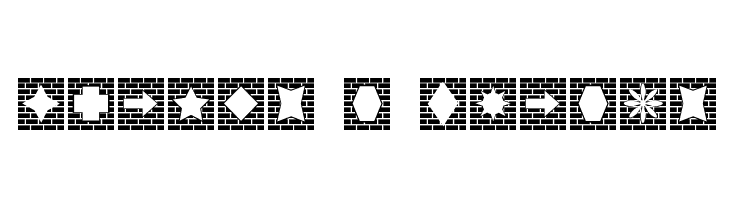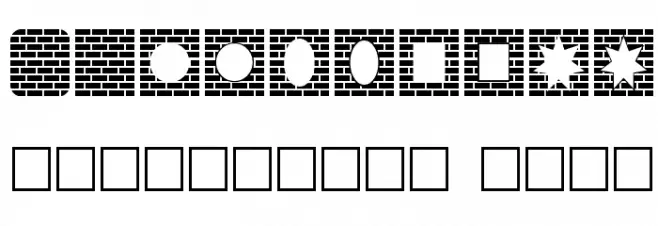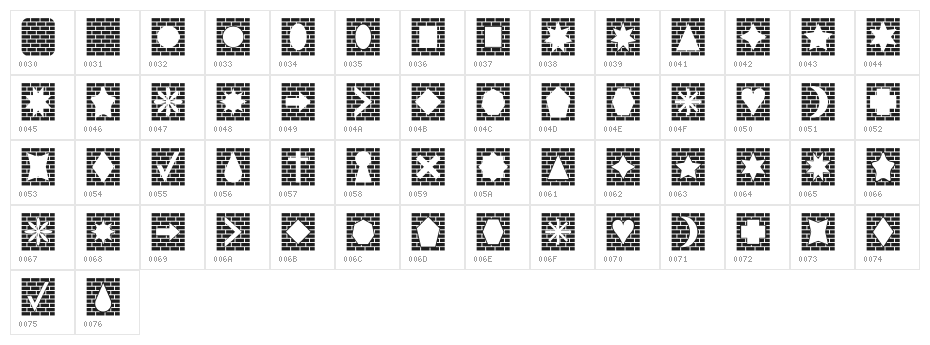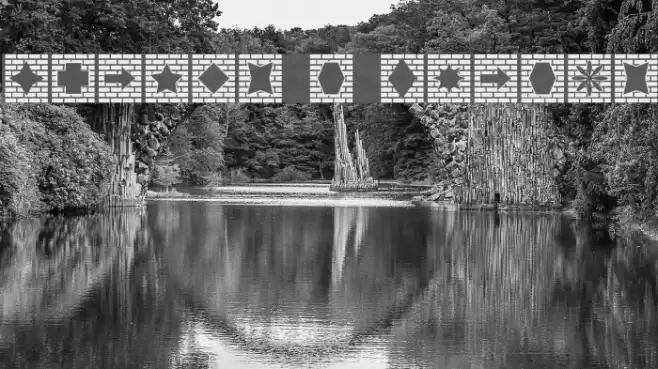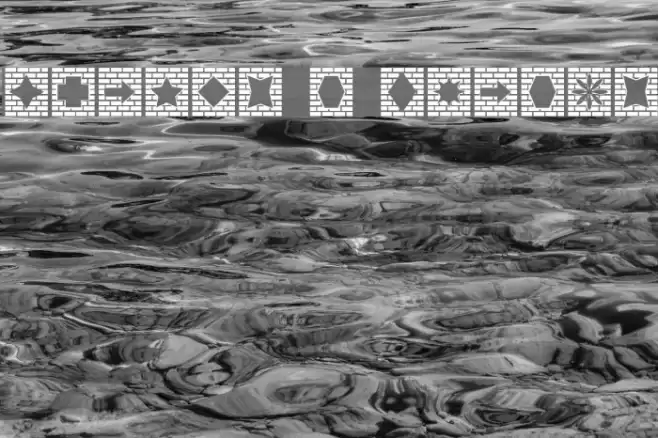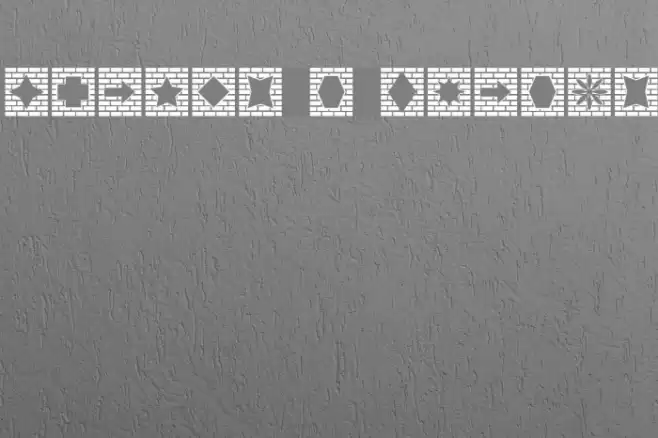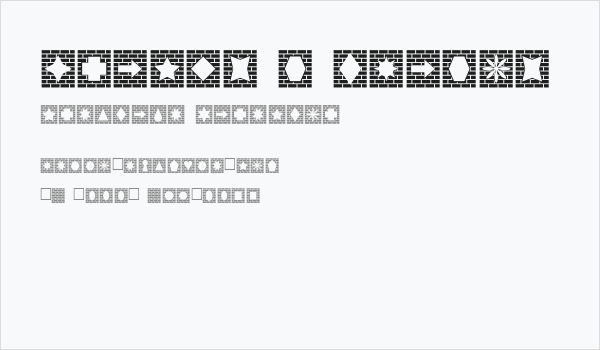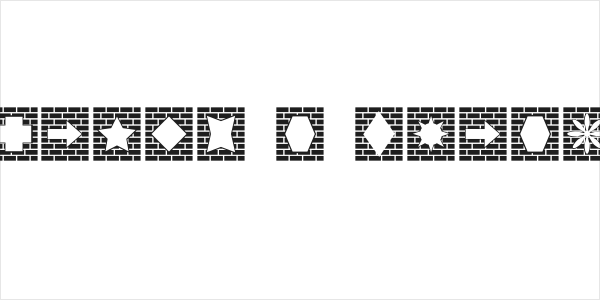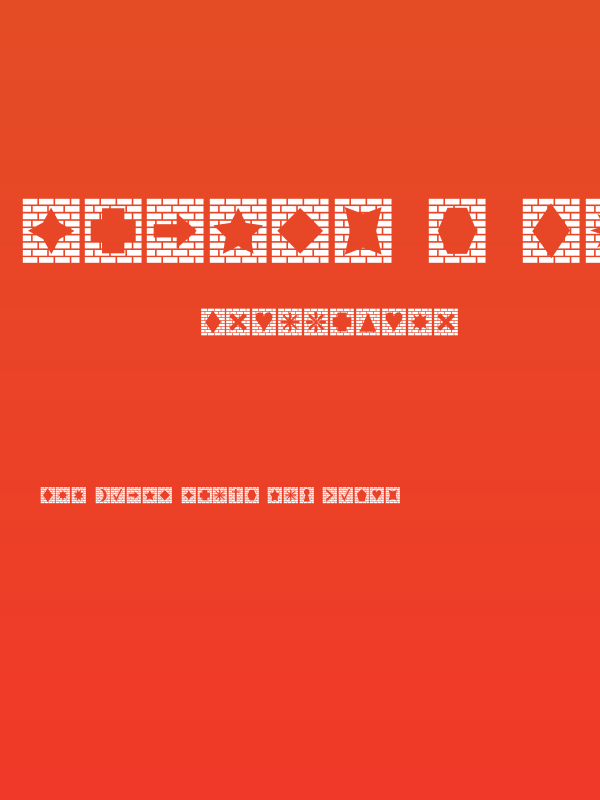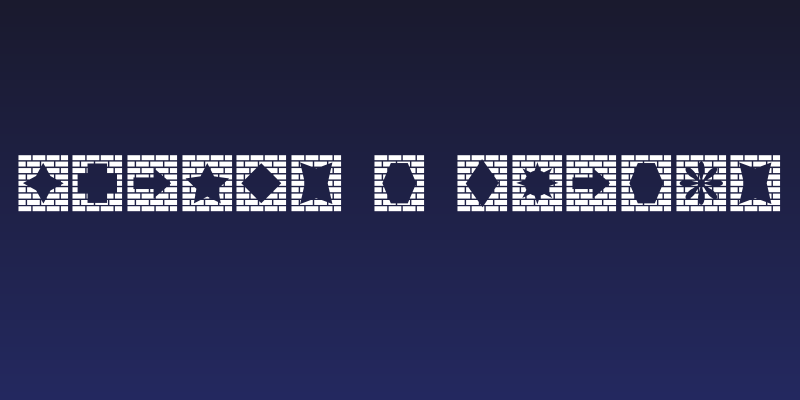
Bricks n Things Font
| Caso d'uso | Decorative elements, graphic design, artistic projects. |
| Progetti proposti | This design could be used for decorative purposes, such as creating unique borders, backgrounds, or artistic elements in graphic design projects. |